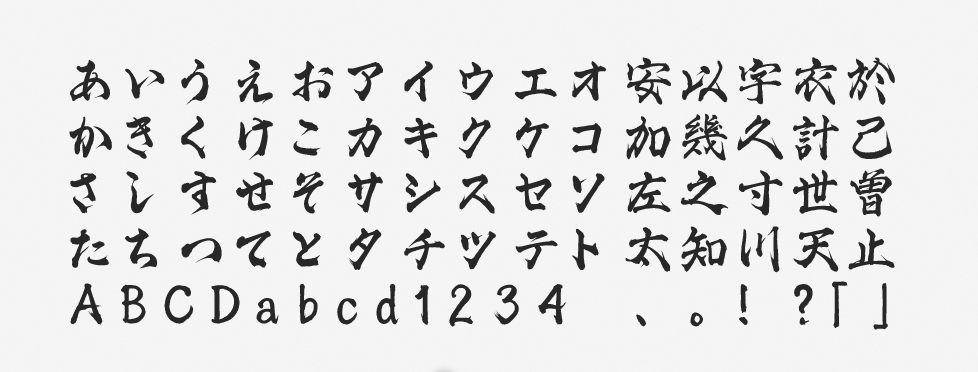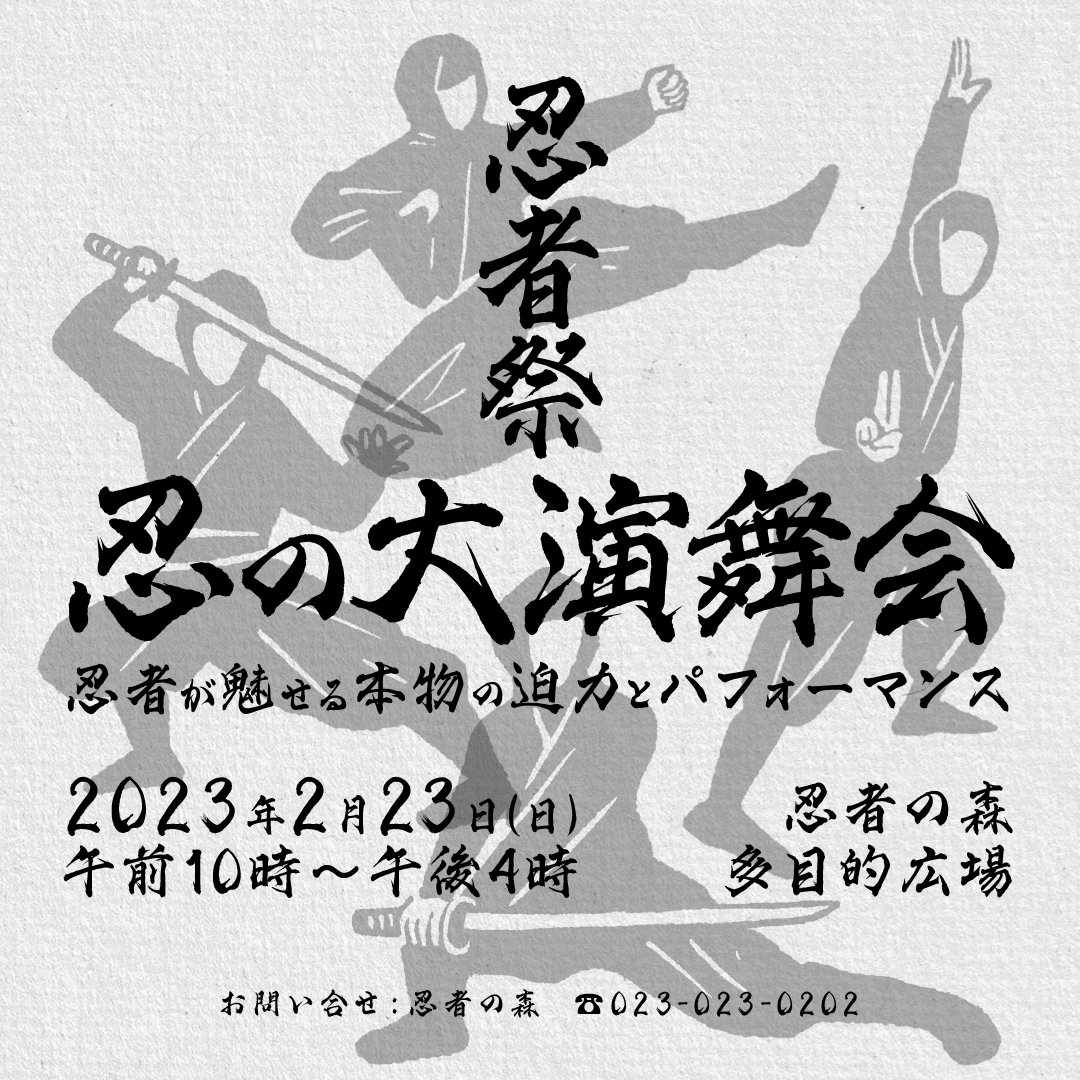
「剣閃」について
剣閃は2019年のモリサワ新書体としてリリースされた筆書系のデザイン書体です。見出し用に作られており、骨太で力強いイメージを備えています。フォント名が「剣」「閃」の文字で構成されているように、鋭いスピード感も特徴。和風のコンテンツで「カッコ良さ」を演出したい場面で活用されています。
「剣閃」の特徴
剣閃では、筆先のニュアンスで躍動感が演出されています。特に暴れ回るような「はね」の筆致は、雰囲気たっぷりです。しかし、それでありながら仮想ボディにはキレイに収まっており、すっきりとした印象も与えます。
「ふところ」がしっかり確保されているため、勢いがありながらも読みやすい珍しいタイプのフォントです。筆書系ならではのしっかりとした“黒み”も特徴で、強いインパクトを出す目的でも役立ちます。
基本的に筆書系のフォントは小さく表示するには不向きですが、剣閃は比較的に小さな文字でも扱いやすいです。縦組みでも横組みでも、文字間隔をツメても広げても読みやすいので、今回の作例のような“和”のイメージで表現する場合には、縦横無尽に使いこなしてみてはいかがでしょうか。
タイトル・見出し、パンフレット、チラシ、POP